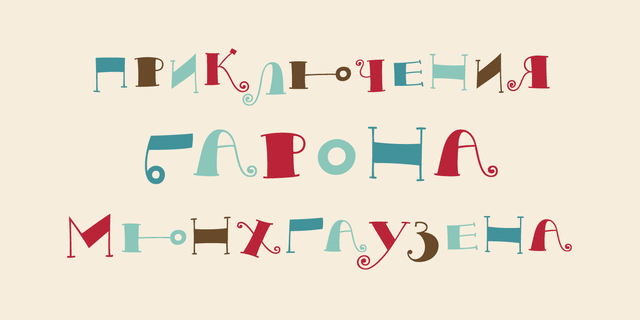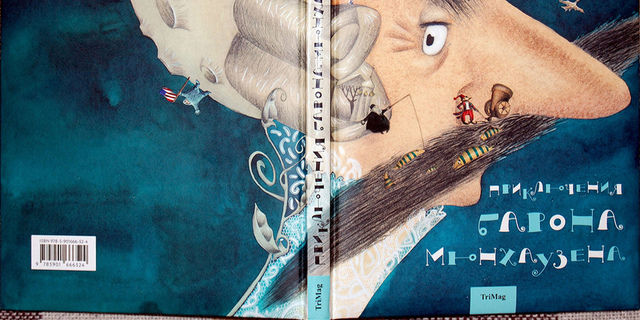
Шрифт Акатик специально создан для заголовков в книжке о бароне Мюнхаузене. Книга издается в издательстве ТриМаг. Шрифт получил диплом 3 степени за совершенство в шрифтовом и графическом дизайне на конкурсе студенческих шрифтовых работ, организованном фирмой ParaType. Шрифт разработала Светлана Акатьева при участии Александры Корольковой в 2008 году.